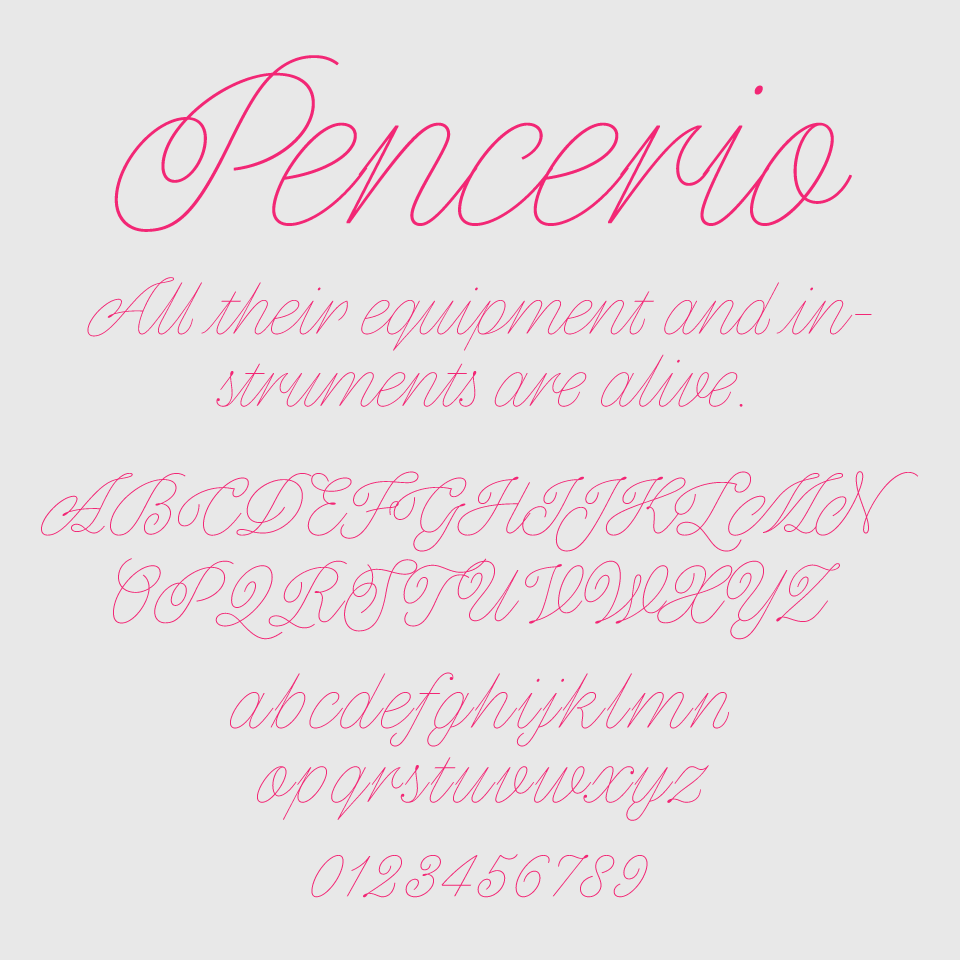
Pencerioフォントは、極細のラインで描かれた優雅なスクリプト体が特徴的なフォントです。線の強弱が少なく、全体に軽やかなトーンで構成されており、まるで空中に描かれたペンの軌跡のような浮遊感があります。
フォーマルというよりも、パーソナルな感情に寄り添うようなタッチが魅力で、ウェディングのペーパーアイテムや、繊細なコスメ系のブランディングなどにもぴったりなフォントです。